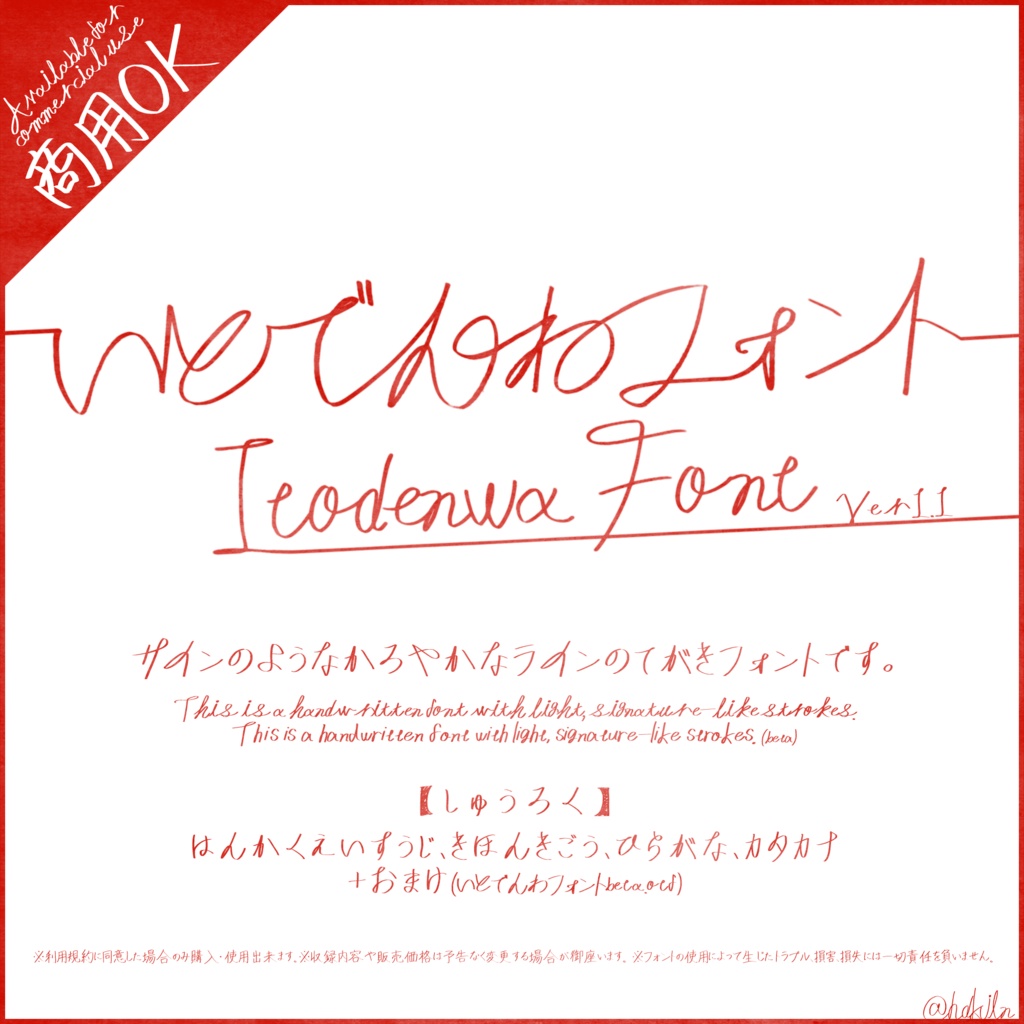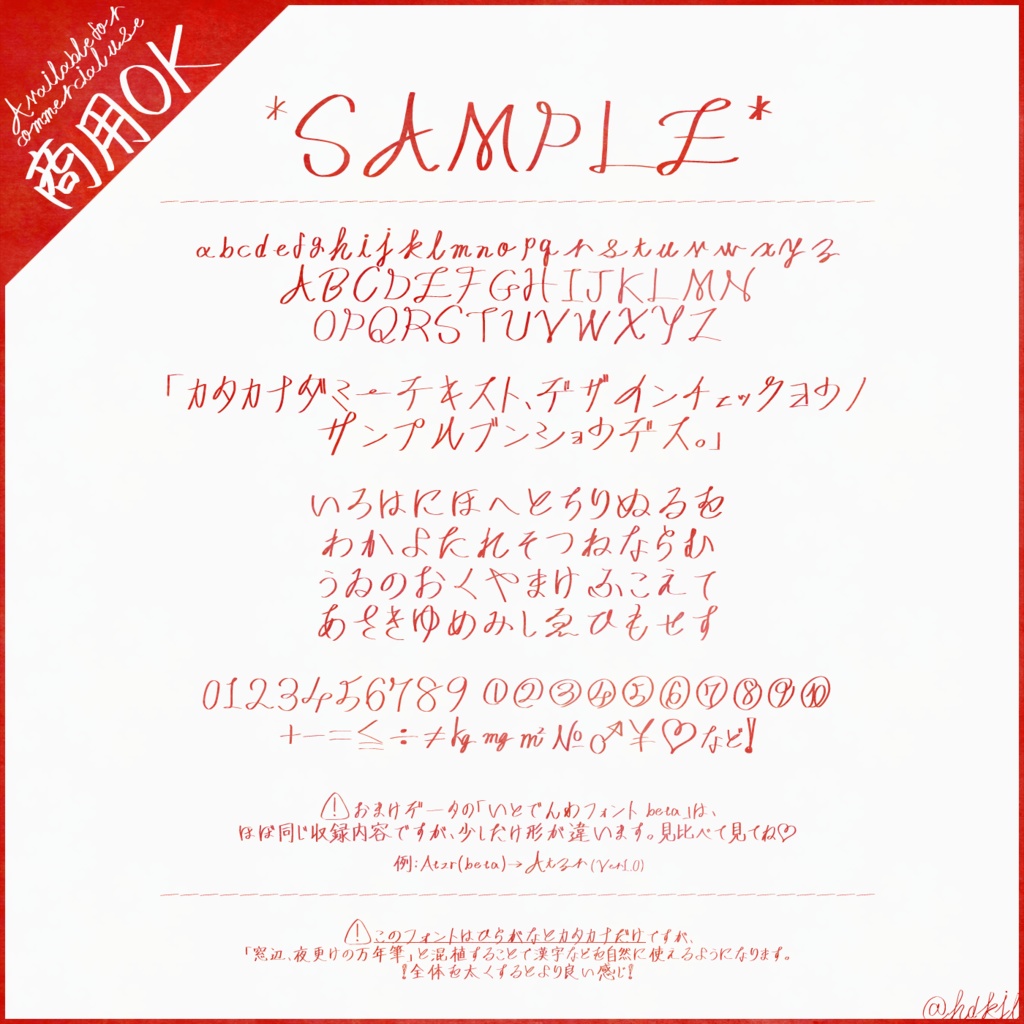
サインのような軽やかなラインの手書きフォントです。 This is a handwritten font with light, signature-like strokes. 【収録】 半角英数字、基本記号、ひらがな、カタカナ、機種依存文字(①~⑩) おまけ:β版.otf(収録範囲は↑とほぼ同じ) ※本フォントの購入者・使用者は利用規約に同意したとみなします。 ーーーーーーーーーー ●フォント形式:OpenTypeフォント ●本フォントは、ばっと but (@buttaiwan) 様の「フォントを書こう! by 字嗨(buttaiwan.github.io)」を利用してフォントを制作しました。 ーーーーーーーーーー ■請求書について■ BOOTHの決済システムを利用しているため、当方から個別の領収書発行は原則行っておりません。購入時に発行されるメールや、マイページの購入履歴をもって代えさせていただきます。 法人間の取引等で、どうしても当方発行の請求書・領収書が必要な場合に限り、例外的にPDF形式での発行を承ります。ご希望の場合は、注文確定前にメールにてご連絡ください。